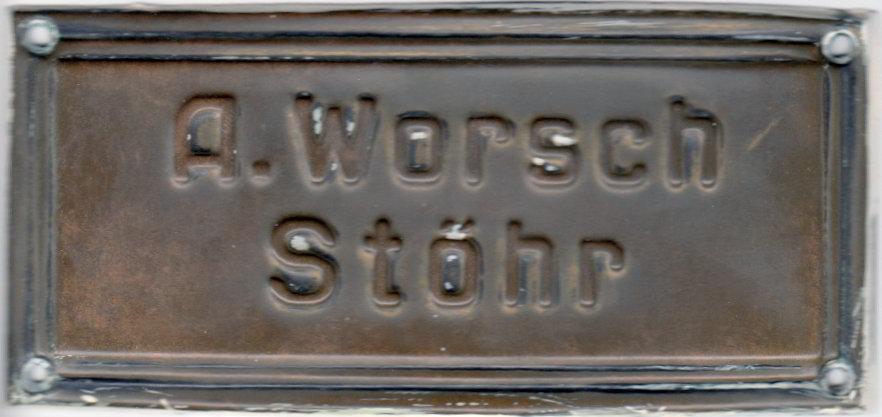
Suche Schriftart dieses Türschilds aus den 1920er/30ern(?)
ich suche eine Schrift, die derjenigen auf dem angehängten Türschild (war an einer Wohnung aus den 1920er/30ern angebracht) möglichst nahe kommt – idealerweise natürlich genau diese Schrift. Sie dürfte auch was kosten, ich brauche sie im Zweifelsfall aber auch gar nicht als Font-Datei.
Die unterschiedlichen Formen der Buchstaben (z.B. h, r) lassen auf Handarbeit schließen. Das heißt natürlich nicht, dass es die Vorlage nicht doch als Font gibt. Nur wird dieser sicher anders aussehen da die Herstellung des Schildes die Buchstabenformen wahrscheinlich beeinflusst hat (z.B. die Rundungen).